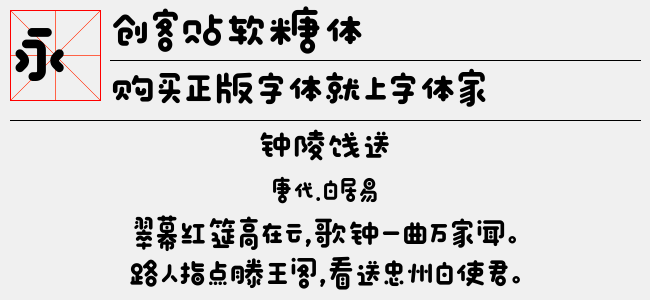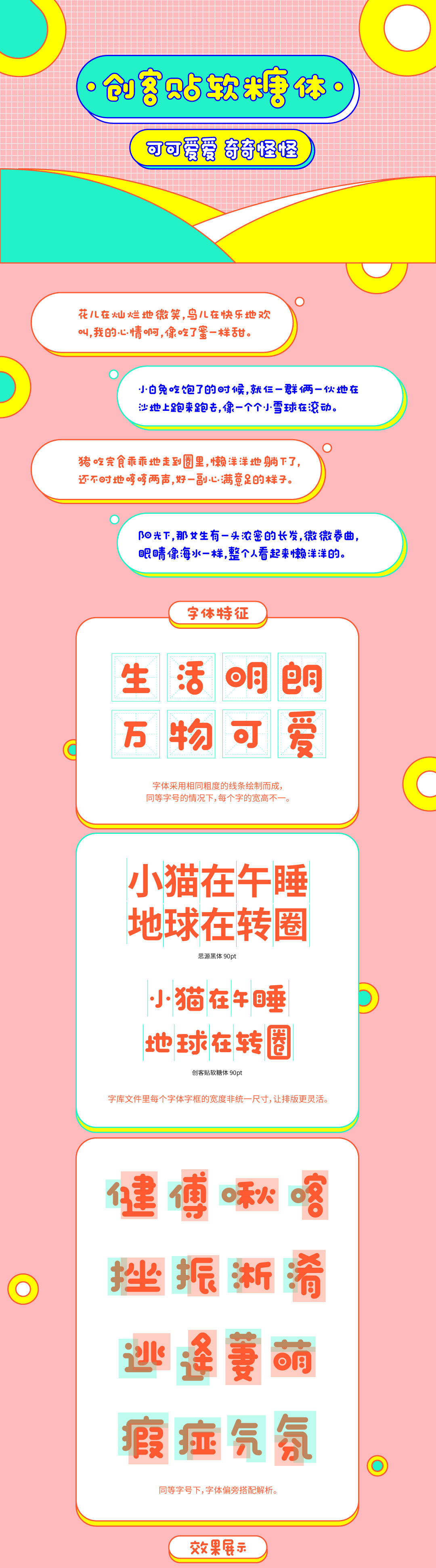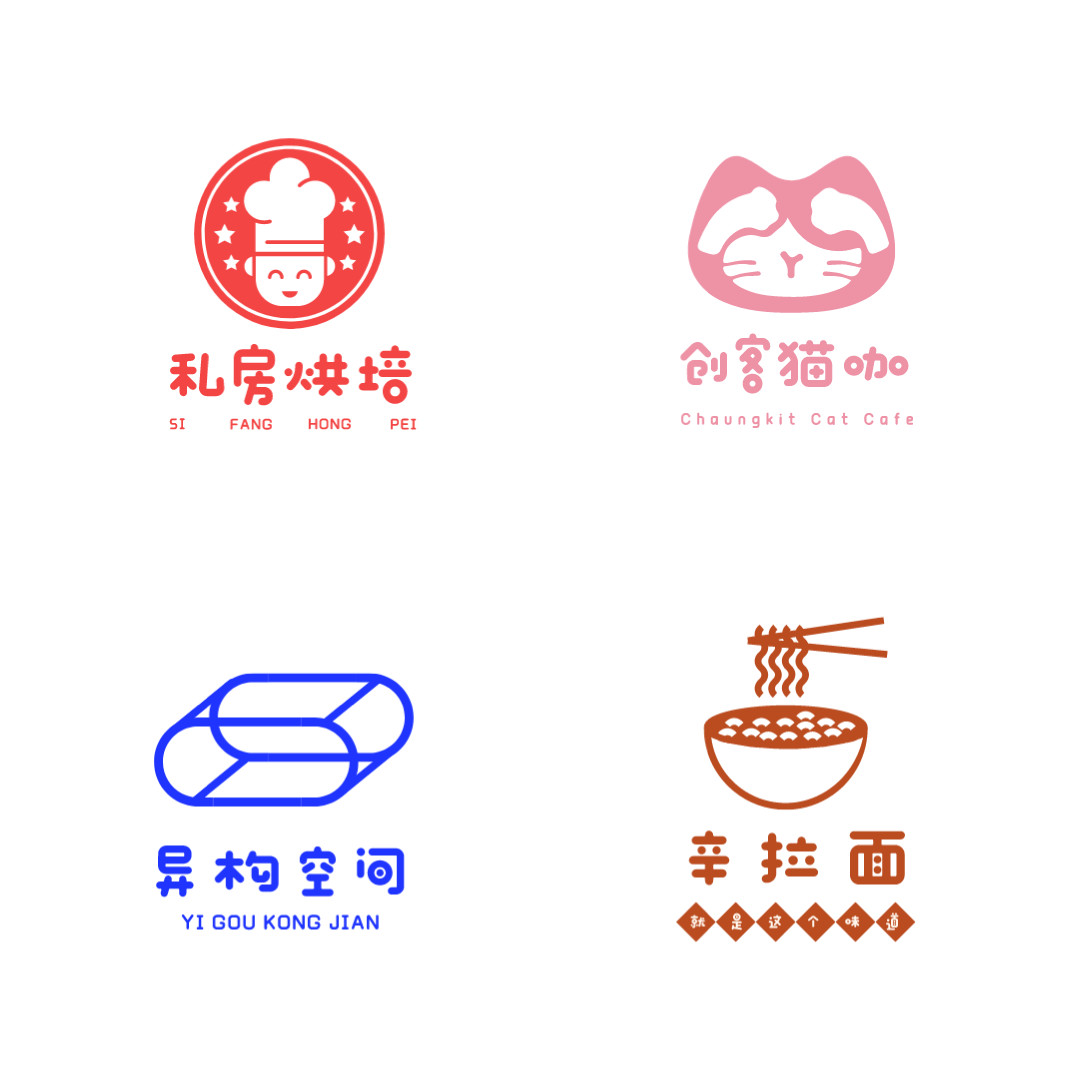
创客贴软糖体
字体作者:创客贴字体
字体名称:创客贴软糖体
字体家族:创客贴
书体类型:手写/印刷类
创客贴软糖体
创客贴软糖体是2020年第四季度的作品了,软软萌萌的外观受到了用户的广泛好评。
本字体基于中华人民共和国GB2312-80字符集标准,采用TrueType和OpenType两种格式,共收容汉字6763个,英文及标点等常用字符814个。
创客贴软糖体 - 送段明府
创客贴软糖体 - 归赴行在过上竺寺偶题
创客贴软糖体 - 千秋万岁
创客贴软糖体 - 大写字母/小写字母/数字